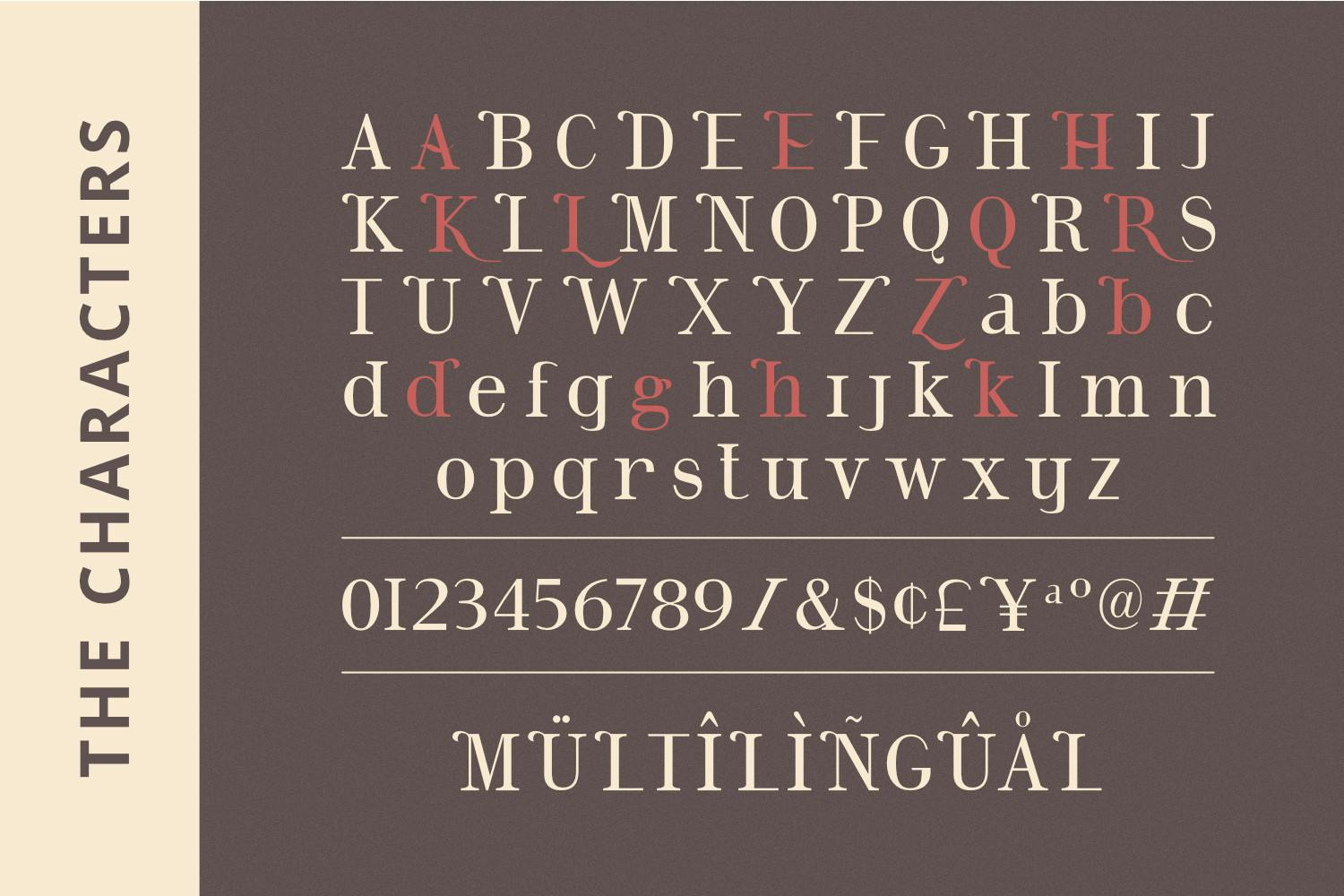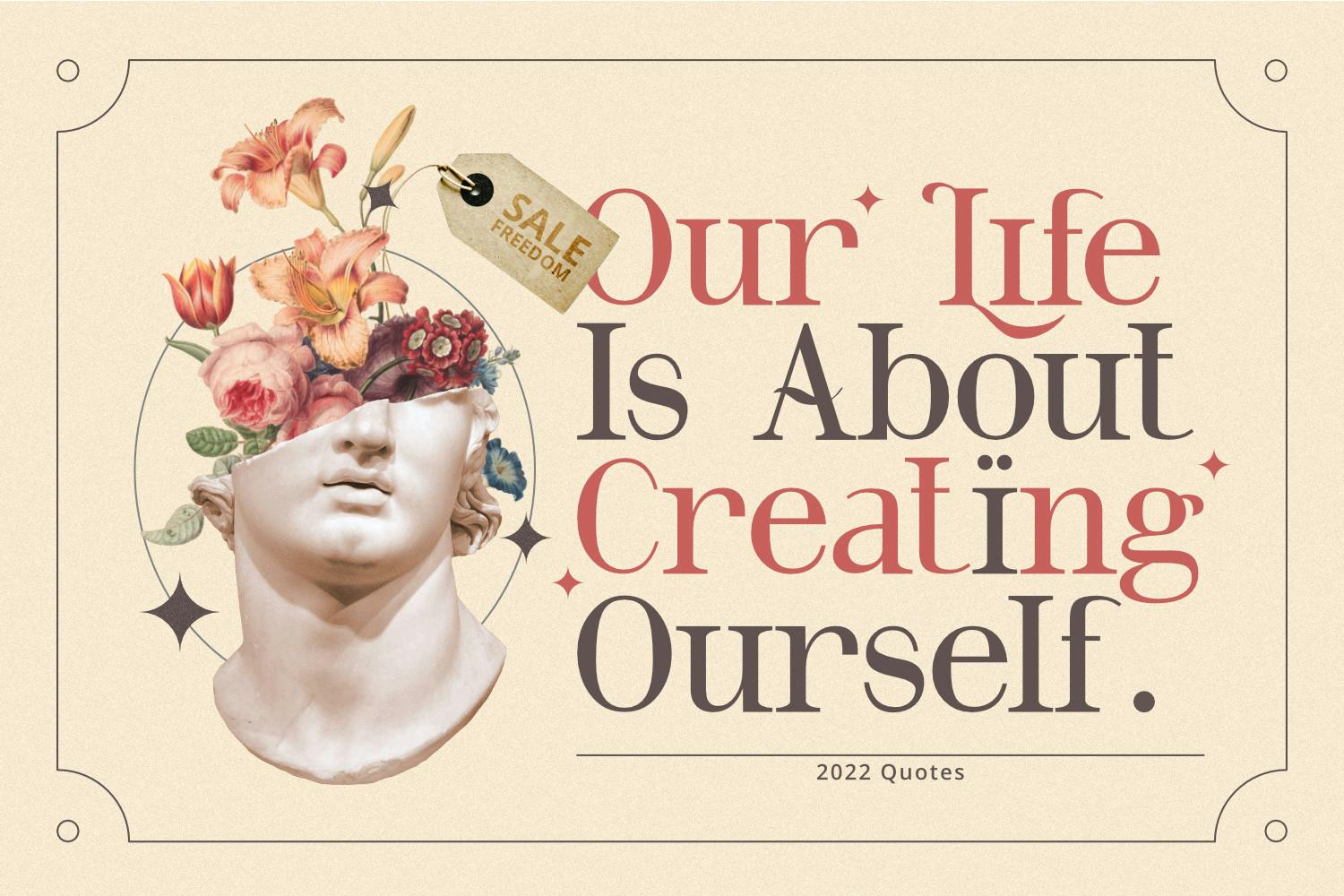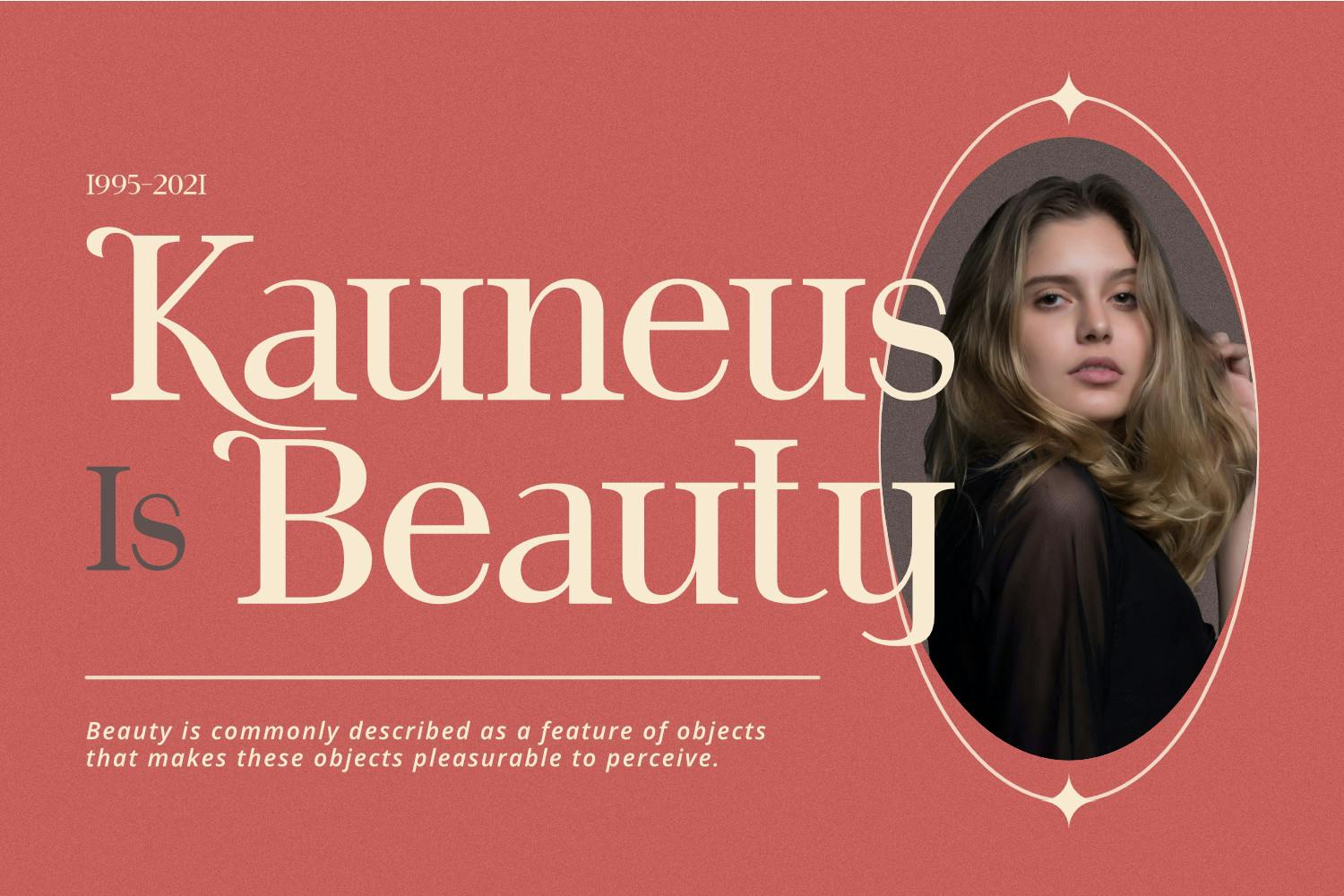
فونت Laophe Font Product برای بسیاری از پروژههای شما مانند طراحی لوگو و برندینگ، عکاسی، دعوتنامهها، واترمارکها، تبلیغات، طراحی محصولات، لوازمالتحریر، طراحی عروسی، برچسبها، بستهبندی محصولات، رویدادهای خاص و بسیاری دیگر مناسب است.